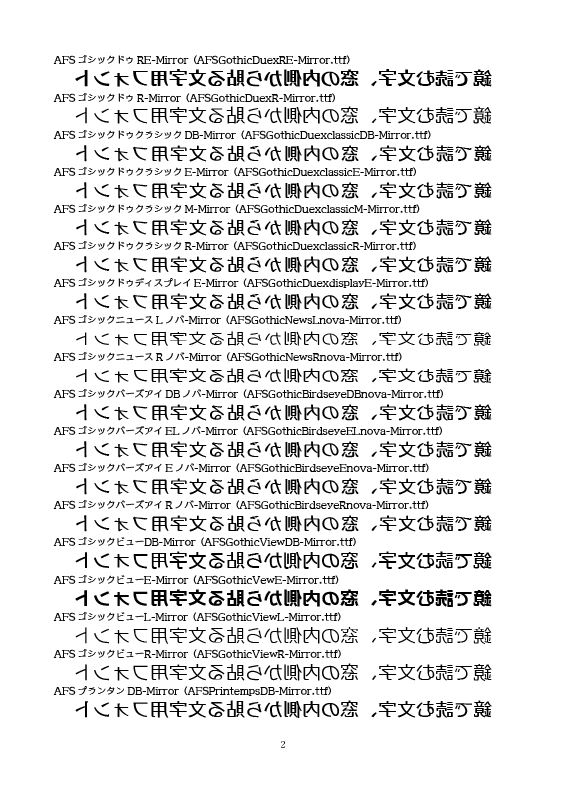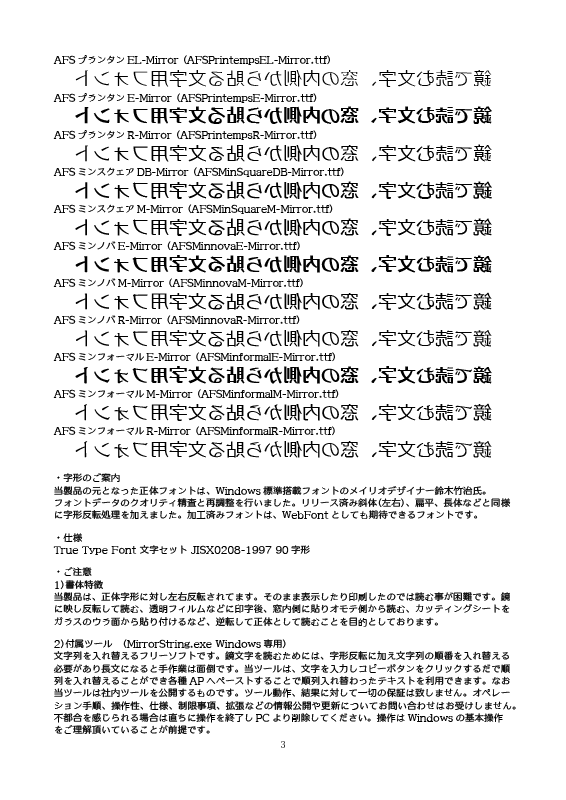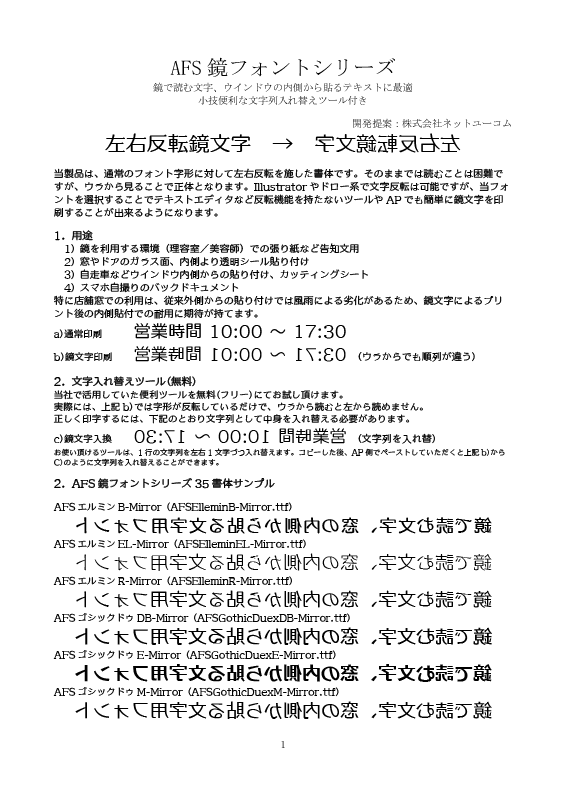
AFS鏡フォント35は左右反転フォント35書体セットです。
テキストエディタなど反転機能を持たないツールやAPでも簡単に鏡文字を印刷出来るようになります。
※プレビューフォントは「AFS エルミンB-Mirror」です。
1.用途
1) 鏡を利用する場所(理容室/美容師)での張り紙など告知文用
2) 窓やドアのガラス面、内側より透明シール貼り付け
3) カッティングシート
4) スマホ自撮りのバックドキュメント
特に店舗窓での利用は、従来外側からの貼り付けでは風雨による
劣化があるため、鏡文字によるプリント後の内側貼付での耐用に
期待が持てます。